วิธีสร้างฟอนต์ทอง ทางลัดง่าย ๆ ไม่เกิน 1 นาที
ดีไซน์เนอร์หลายบางกลุ่มที่ใช้ชีวิตส่วนใหญ่ไปกับการทำงานที่มินิมอลมีสไตล์ ต่างก็มาตายหากเจอบรีฟประเภท “พี่ขอเรียบหรู ดูแพง” ฟอนต์สีทองเป็นไอเดียแรกที่อาจจะวิ่งขึ้นมาในหัวเราทันที แต่กว่าจะเป็นฟอนต์ทองที่ดูเป็นทองนั้น จะให้มานั่งทำเองถือว่าใช้เวลาและเป็นเรื่องยากมากเลยทีเดียว
วันนี้ Portjolio จะมาบอกทางลัดการเสกฟอนต์สีทอง ที่ดูมีมิติประหนึ่งนำทองแท่งมาทำฟอนต์ เพื่อส่งตรงถึงลูกค้าภายใน 1 นาที ด้วยเทคนิคที่เรียกว่า “บารมี freepik” ขั้นตอนเป็นอย่างไรไปดูกัน
ขั้นตอนที่ 1
เข้าเราเข้าไปที่เว็บไซต์ freepik สุดยอดคงคลังสำหรับหนุ่ม ๆ สาว ๆ ชาวดีไซน์เนอร์อย่างพวกเรา จากนั้นพิมพ์ที่ช่องค้นหาด้วยคีย์เวิร์ด font gold psd เพียงเท่านี้ทุกอย่างก็จะพาเราไปอยู่ร้านทองทันที
ขั้นตอนที่ 2
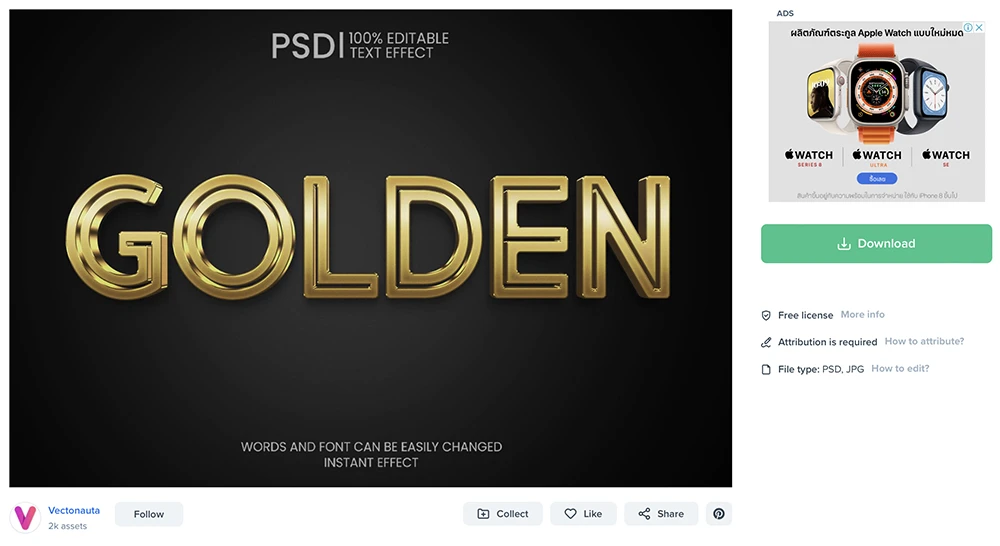
ขั้นตอนที่ 3
แตกไฟล์ที่ zip ไว้ออกมา จากนั้นก็ทำการเปิดไฟล์ .PSD ที่คุ้นเคยขึ้นมา คุณจะเห็นตัวอย่างฟอนต์ทองที่เราเลือกไว้ จากนั้นมองหา Layer ที่มักจะเขียนว่า “YOUR TEXT HERE” ดับเบิ้ลคลิกเพื่อเข้าสู่ขั้นตอนการแก้ไข
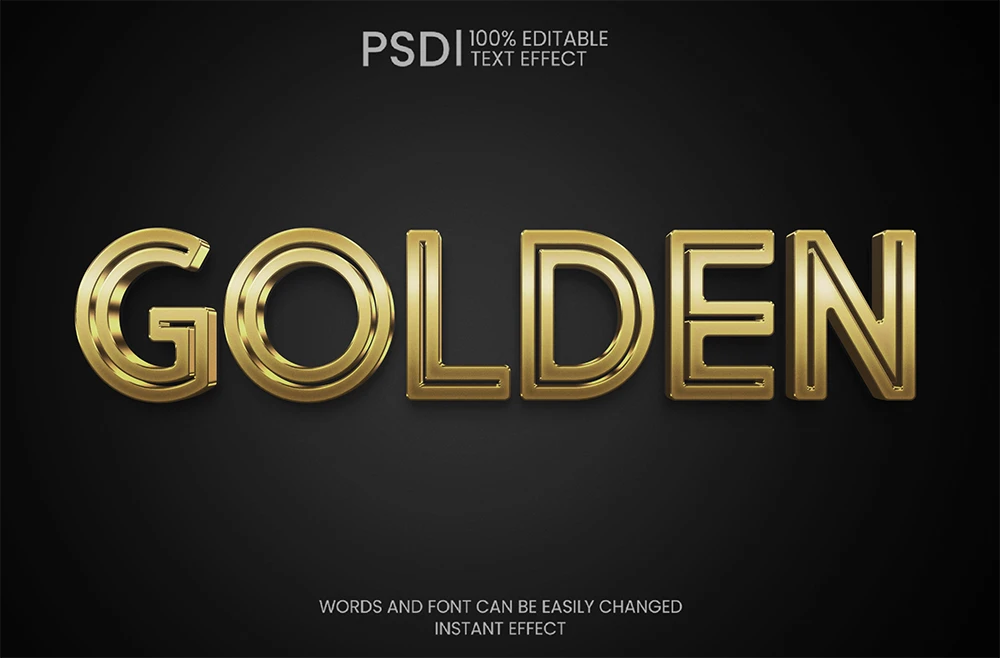
ขั้นตอนที่ 4
ทำการแก้ไขข้อความและฟอนต์ตามที่เราต้องการ หรือจะโยนไอคอนหรือ Vector มาแทนตัวอักษรก็ได้ จากนั้นให้กด Save และกลับไปหน้าต่างก่อนหน้า
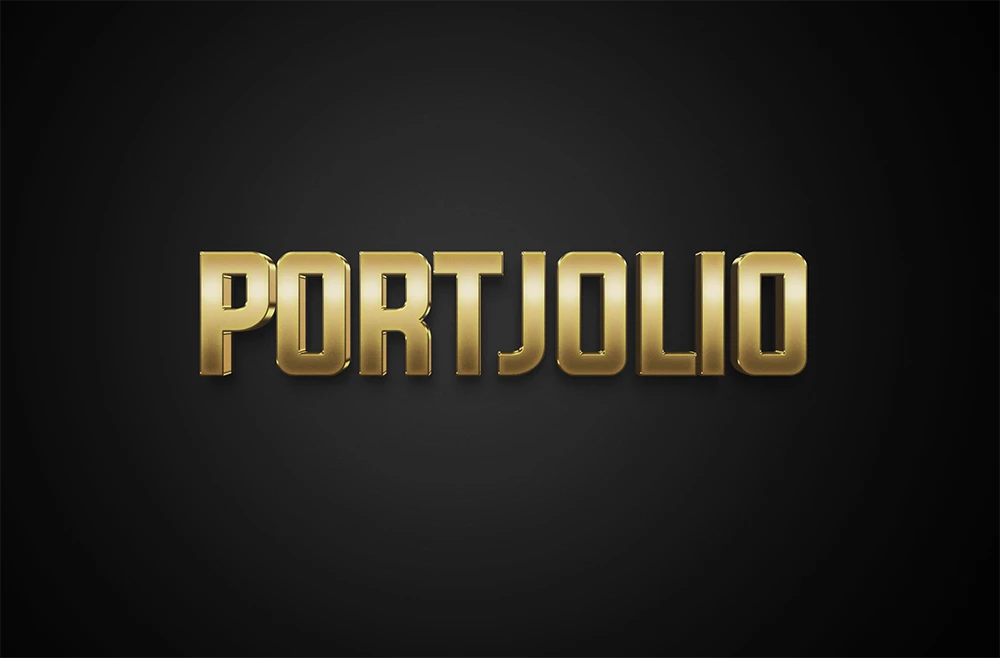
เพียงเท่านี้เราก็จะได้ฟอนต์สีทอง ดูหรูดูแพง ไฮโซ ไฮซ้อ อะไรก็ตามแต่ แถมอีกหนึ่งเคล็ดลับที่จะเสริมความแพงนี้ ด้วยการใส่แสง ใส่แฟร์เข้าไป ซึ่งก็โหลดได้ฟรีจาก freepik เช่นเคย เพียงเท่านี้ก็จะยิ่งทำให้เสริมบารมีให้งานชิ้นนี้สมบูรณ์ยิ่งขึ้นไป!!